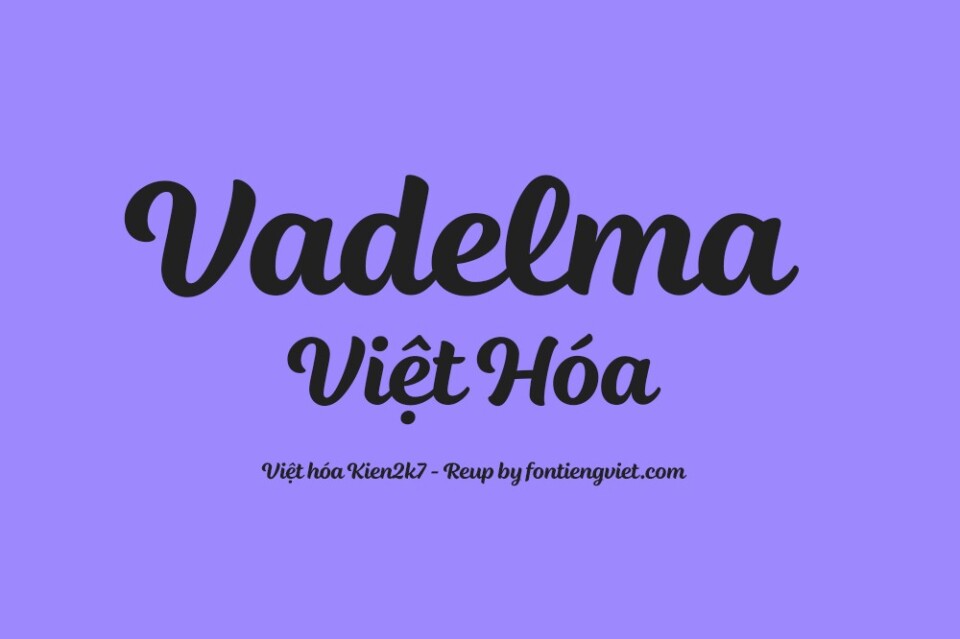
Font Việt Hoá Vadelma
Trong thế giới thiết kế đồ họa hiện đại, việc tìm kiếm một bộ Font Việt Hoá Vadelma chất lượng luôn là ưu tiên hàng đầu của các bạn học sinh và giáo viên. Đây là một mẫu Font Miễn Phí mang phong cách script viết tay mềm mại, giúp các bài thuyết trình hay thiệp chúc mừng trở nên sinh động và gần gũi hơn. Font Việt Hoá Vadelma không chỉ sở hữu những đường nét thanh mảnh, uyển chuyển mà còn được tinh chỉnh tối ưu để hiển thị hoàn hảo các dấu tiếng Việt mà không xảy ra lỗi phông chữ phổ biến.
Đặc điểm nổi bật của Font Việt Hoá Vadelma trong học tập
Phong cách thủ công đầy ấn tượng
Font Việt Hoá Vadelma nổi bật với những nét vẽ tự nhiên như dùng bút mực viết trên giấy. Sự kết hợp giữa các đường nối chữ tinh tế tạo nên cảm giác nghệ thuật cao, giúp các nội dung trang trí tiêu đề bài học trở nên bắt mắt. Đặc biệt, bộ font này rất phù hợp cho các dự án thiết kế thiệp mời, bìa sổ tay hoặc các slide bài giảng cần sự sáng tạo đột phá. Độ dày của nét chữ được tính toán kỹ lưỡng, đảm bảo tính thẩm mỹ ngay cả khi in ấn trên khổ giấy nhỏ.
Khả năng tương thích và dễ sử dụng
Cách ứng dụng Font Việt Hoá Vadelma hiệu quả
Để tận dụng tối đa vẻ đẹp của bộ chữ này, bạn nên sử dụng chúng cho các đoạn văn ngắn hoặc tiêu đề chính. Việc kết hợp Font Việt Hoá Vadelma với các phông chữ không chân (Sans-serif) sẽ tạo ra sự cân bằng thị giác tuyệt vời. Đây thực sự là món quà ý nghĩa từ <a href="https://fontmien